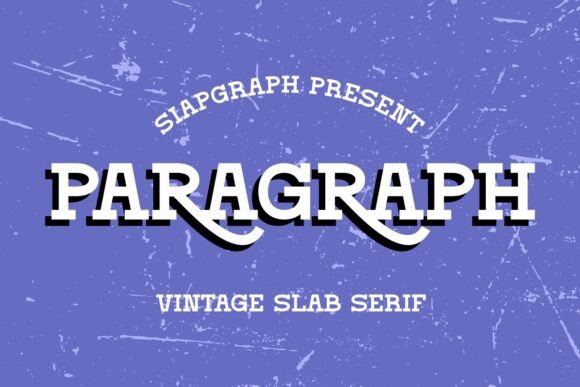
Paragraph
์˜ฌ๋ฐ”๋ฅธ ๋””์ž์ธ ์š”์†Œ๋ฅผ ์ฐพ๋Š” ๊ฒƒ์€ ์–ด๋ ค์šธ ์ˆ˜ ์žˆ์ง€๋งŒ Paragraph๋Š” ์ž‘์—…์„ ์ฆ‰์‹œ ํ–ฅ์ƒ์‹œํ‚ค๋Š” ๋›ฐ์–ด๋‚œ ์ปฌ๋ ‰์…˜์„ ์ œ๊ณตํ•ฉ๋‹ˆ๋‹ค.
POD(์ฃผ๋ฌธํ˜• ์ธ์‡„) ์ œํ’ˆ, ๊ฒฐํ˜ผ์‹ ์ดˆ๋Œ€์žฅ ๋˜๋Š” ์†Œ์…œ ๋ฏธ๋””์–ด ๊ทธ๋ž˜ํ”ฝ์„ ๋งŒ๋“ค ๋•Œ Paragraph๋Š” ์ด์ƒ์ ์ธ ์„ ํƒ์ž…๋‹ˆ๋‹ค.